Die norwegischen Schriftgestalter Frode Helland und Sindre Bremnes sind gerade mit dem neuen Schriftenlabel Monokrom an den Start gegangen. Bislang sind 5 Schriftfamilien verfügbar, die allesamt gestalterisch und qualitativ überzeugend daherkommen. Die Schriftschnitte sind ab 60 Euro verfügbar.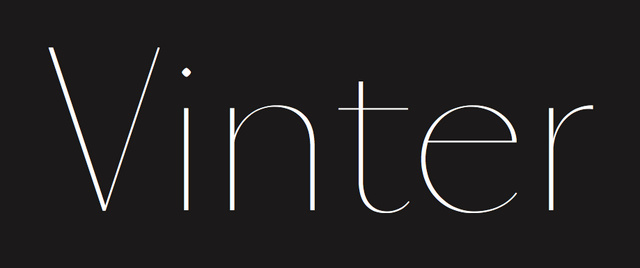
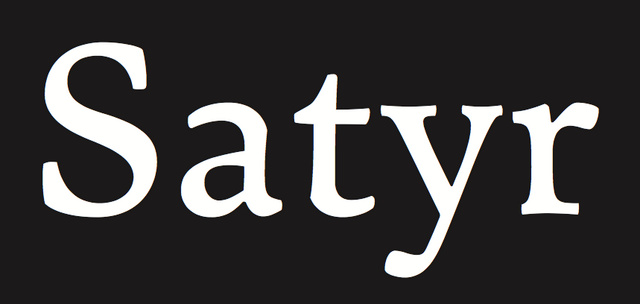
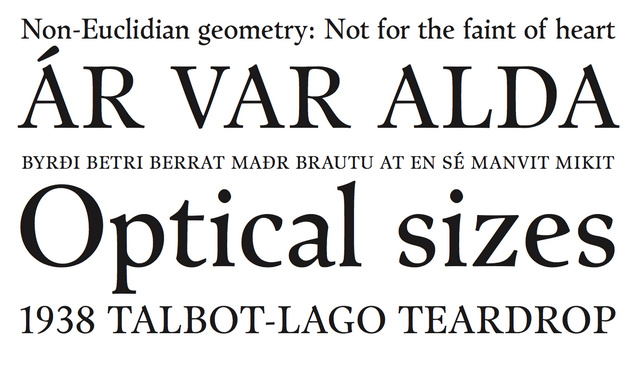
Aus deutscher Sicht interessant: Sämtliche Schriften von Monokrom kommen mit Versal-Eszett.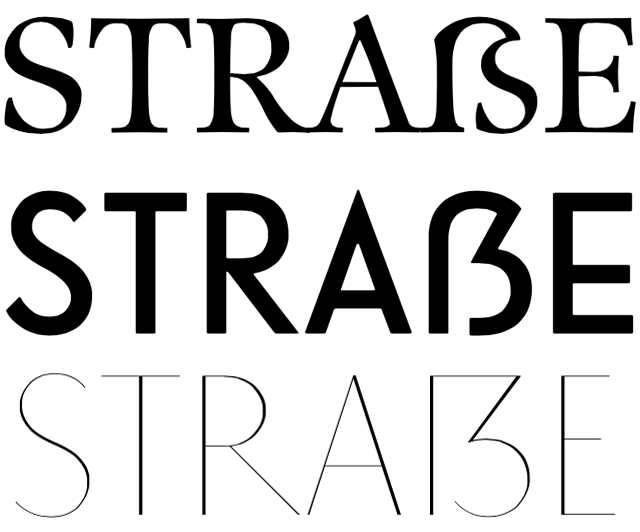
Monokrom: neue Foundry aus Norwegen